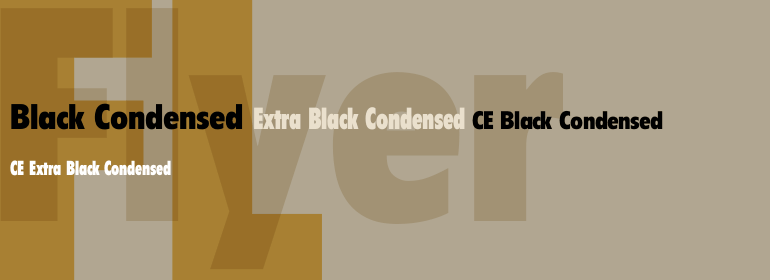
Flyer™
Flyer™,这款字体结构工整、笔画清晰,兼顾美观与易读性,适用于标题、正文、海报、包装、LOGO 等多种场景。字形优雅稳定,风格百搭耐看,适配日常排版与创意设计,让文字呈现更舒适、更具质感。Flyer™一笔一画,皆是细节,以均衡的比例、流畅的线条打造舒适视觉体验,字形端正大气,风格简约现代。无论是商业设计、品牌宣传还是日常排版,都能轻松驾驭,让文字更有格调与力量。Flyer™字体下载。
字体品牌: Linotype(Monotype) 设计师:Linotype Design Studio 字体分类:无衬线体 字体属性:外文 字符集:Unicode 发布时间: 2018